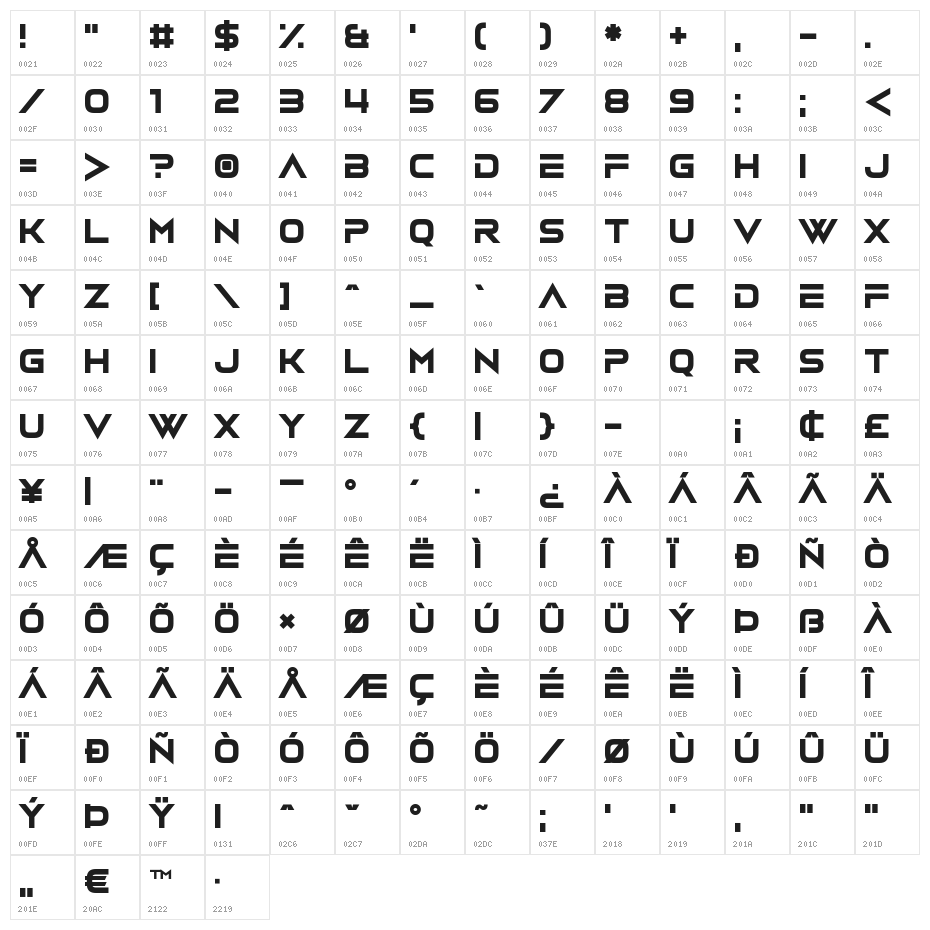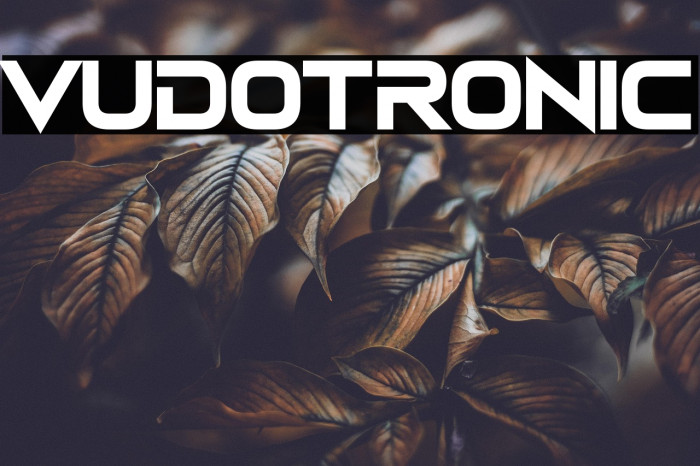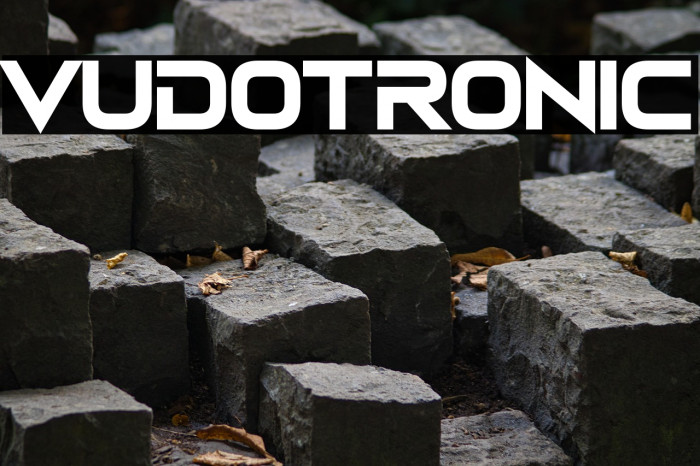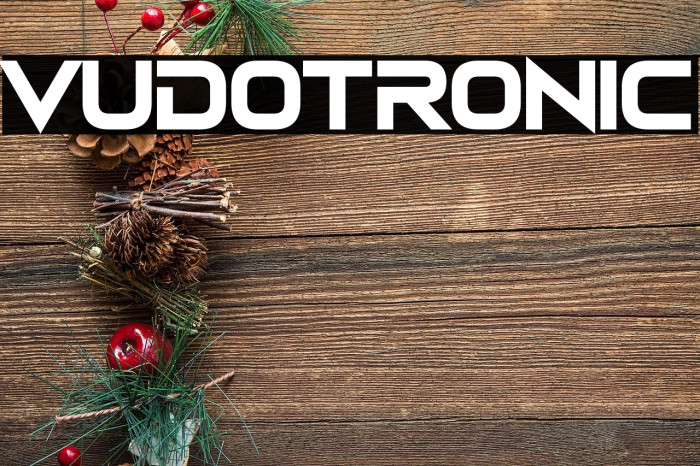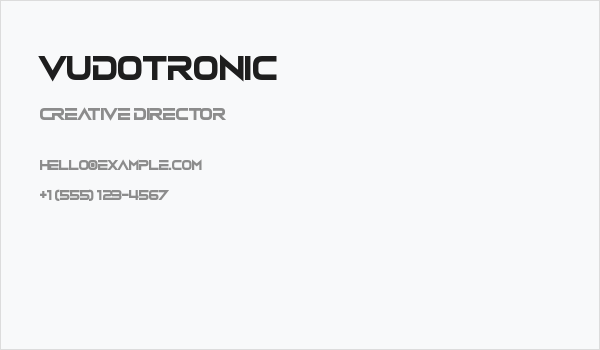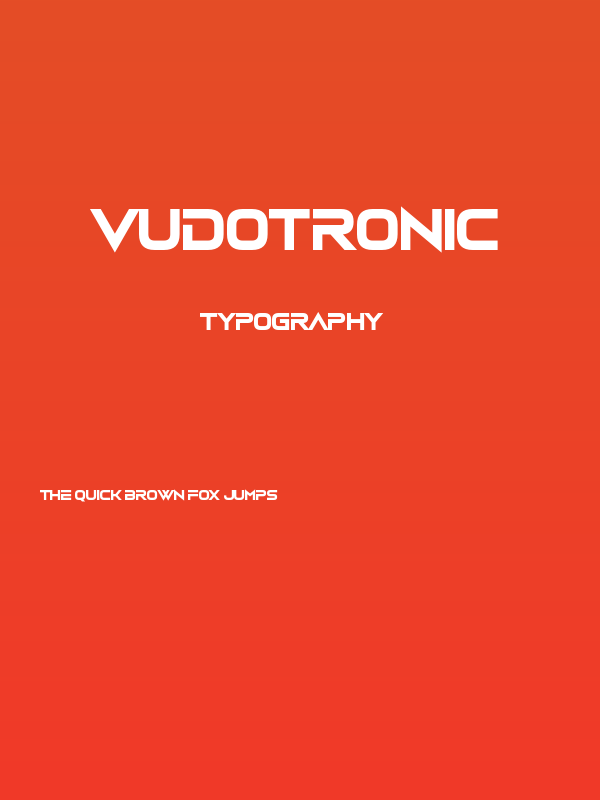
Vudotronic Font
✎ Futuristic
| Anwendungsfall | Headlines, Logos, Display text |
| Vorgeschlagene Projekte | Ideal for tech branding, sci-fi themed designs, video game interfaces, and modern advertising. |